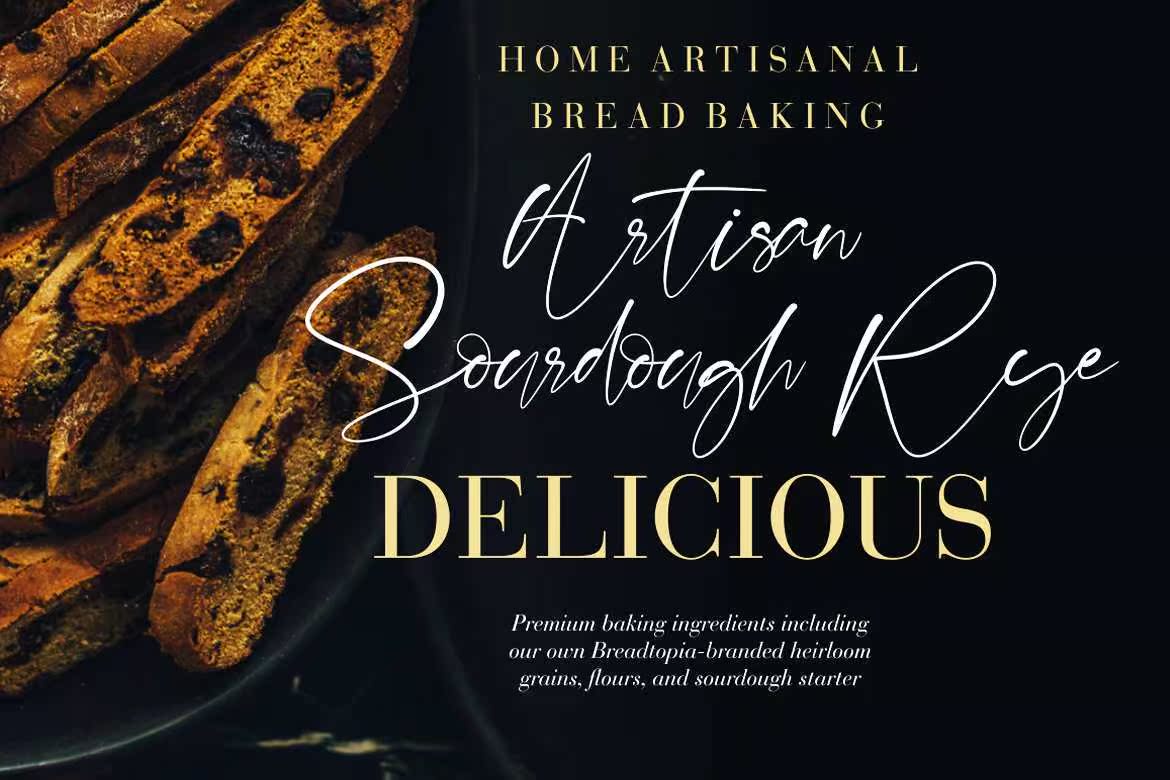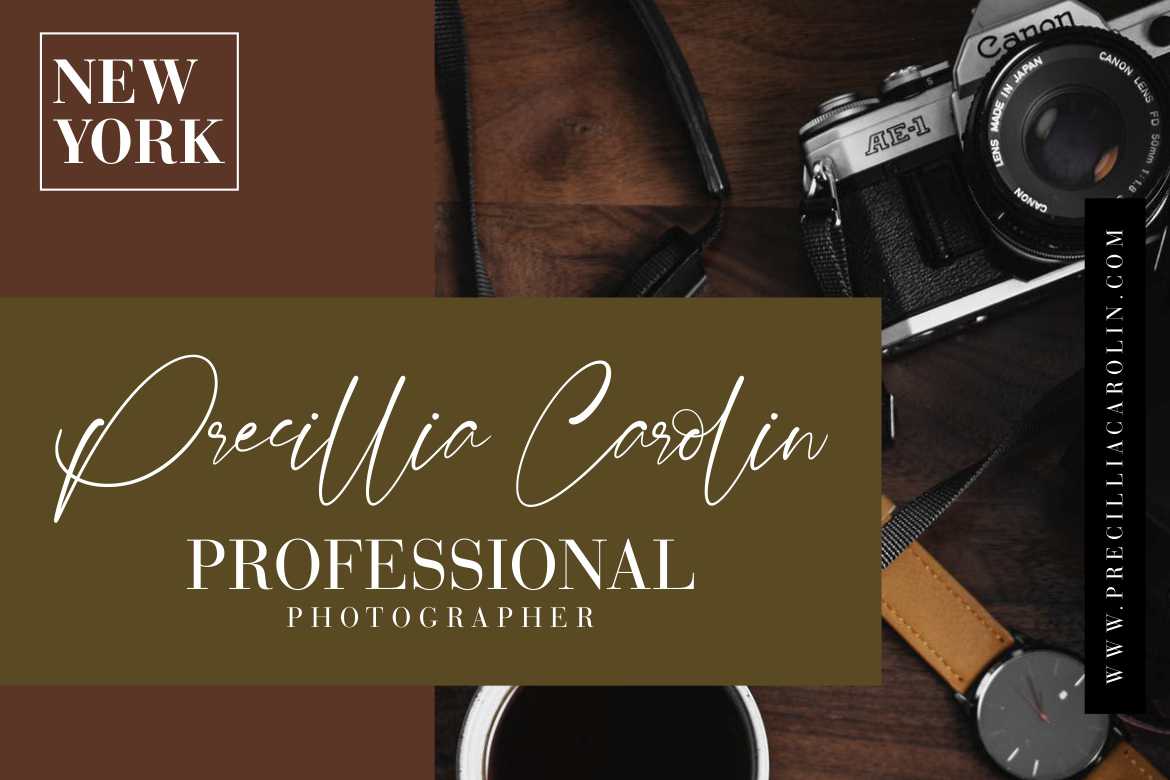
BalistonesaBeautiful,Clean Modern,WriteTenscript Font with Manyligator。此字体中有几个可选的清洗选项。让我们使用此选项创建一些可选的Beautiful项目。BalistonesaBeautiful,Clean Modern,Writenscript Font with Manyligator。此字体中有几个可选的清洗选项。让我们使用此选项创建一些可选的Beautiful项目。